在设计卡通LOGO时,字体的选择对于传达品牌形象和情感起着至关重要的作用。要创造出一个具有治愈感的卡通LOGO,需要选择适合该品牌的字体,并在设计中运用柔和的色彩和形状。
今天我们来介绍几款常见的卡通字体,华光布小兜体 精, Aa鹅卵石, 和白云要吃糖 等。这些字体都有一些共同特点,如圆滑的曲线和简洁的线条,使得它们在视觉上具有愉悦和友好的感觉。
华光布小兜体 精是一款创意卡通字体。可以使文字排版内容活泼可爱、充满个性。字体风格充满童趣,带弧度的竖笔和具有大弯度的笔画设计能够营造出活泼顽皮且带手写意味的风格。
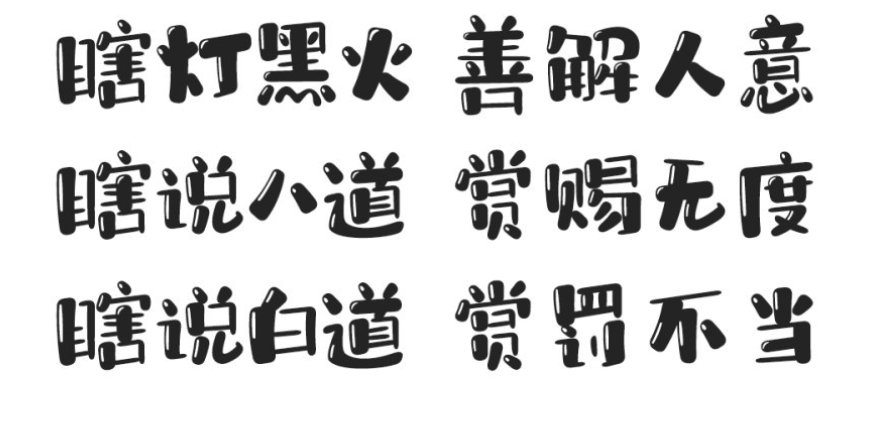
Aa鹅卵石不仅口等封闭部件呈三角形,一头宽一头窄的笔画也都是圆润的三角形,如同鹅卵石的堆叠,可爱有趣,充满卡通感。
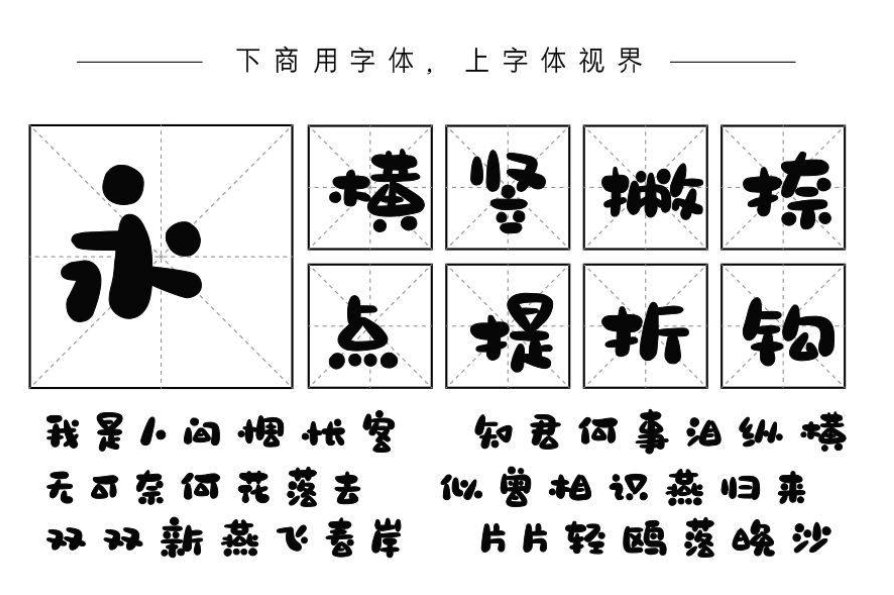
白云要吃糖设计出极贴近白云主题的笔画部件,时而敦厚可爱,时而纤细轻巧,别具一格。宽松的中宫,中偏下的重心,加上活泼俏皮的字形,使得该字具有良好的视觉体验。适用于少儿类书刊,及现代诗歌、短文的排版以及文化、商业类品牌的广告语设计。
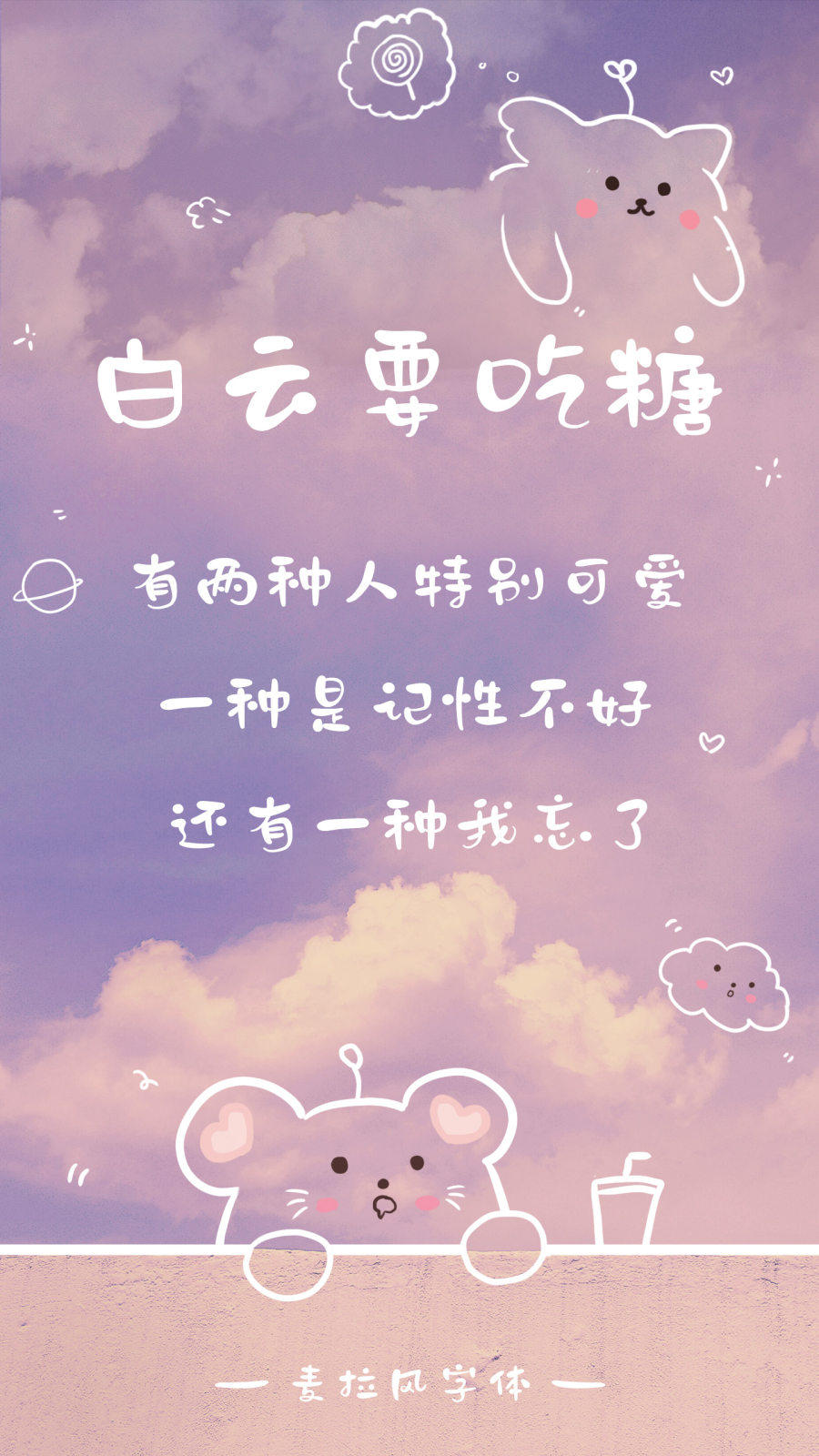
在选择卡通字体时,还需要考虑品牌的主题和情感。如果品牌定位是治愈感,可以考虑使用一些柔和的颜色,如粉色或淡蓝色,并选择一些流畅、优美的字体。
一个治愈感的卡通LOGO应该是简洁、易于识别和具有品牌个性的。它应该能够引起人们的共鸣,并让人们感到愉悦和安心。